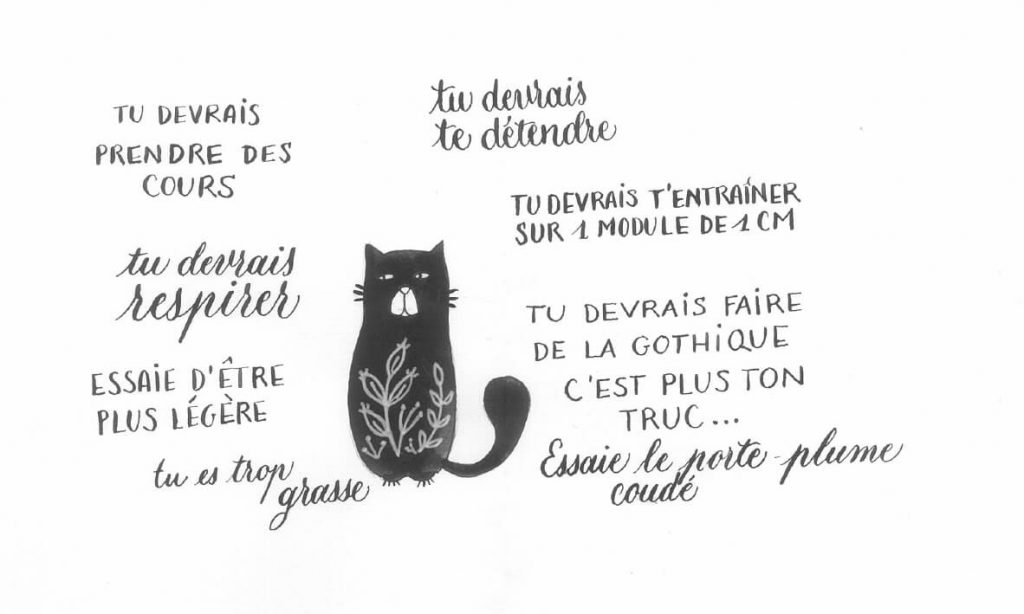
Débuter l’anglaise : quelle encre utiliser ?
Mes premiers pas avec l’anglaise ont été assez désastreux, un peu comme une rencontre qui tourne mal ou un premier baiser qui vous laisse un gout de saucisson dans la bouche. J’aurais pu laisser tomber et retourner à mes écritures gothiques, mais l’appel des volutes aériennes de l’anglaise a été plus fort.
Légèreté, élégance et régularité : voici les maîtres mots pour une belle écriture anglaise, et cela nous fait une belle jambe parce que pour y arriver il faut beaucoup, beaucoup de pratique. On peut donc rajouter « persévérance » !
Les caractéristiques de l’anglaise
Pour mieux comprendre les difficultés du débutant face à l’anglaise, reprenons ses 4 grands principes.
1. Elle est tracée avec une plume pointue
2. Les lettres présentent un contraste plein/délié
3. La forme de base est l’ovale
4. Elle est inclinée, à 54 degrés
Chacune de ces caractéristiques a été pour moi un vrai challenge. Et pour être honnête, mes connaissances des autres écritures ne m’ont pas beaucoup aidée ! Comme je l’ai déjà expliqué dans un article précédent, la première étape a consisté pour moi à :
1. Trouver une plume agréable à utiliser (la Nikko G)
2. M’approprier les pleins et les déliés avec une écriture droite (la Candy Girl).
J’ai ensuite suivi quelques conseils avisés des copines et recommandations lues dans des livres ou sur internet…
L’influence du medium sur l’écriture
Et puis un jour, j’ai compris à force d’essais divers, que l’encre avait une influence déterminante sur le contraste plein/déliés, et sur l’élégance de l’écriture. Avec des plumes larges et biseautées utilisées pour les gothiques ou les onciales, on gagnera en finesse avec une encre bien fluide.
Avec une plume pointue, on aura besoin d’une encre fluide aussi, mais un peu plus consistante, et qui a une bonne adhérence sur la plume (sinon elle coule en grosse goutte et c’est la tâche assurée).
Préparation de la plume
Il faut bien sûr que la plume soit bien propre et dégraissée. Lorsqu’on la trempe dans l’encre, celle-ci doit plus ou moins recouvrir la surface de la plume. S’il y a un effet de goutte d’eau, c’est soit que la plume a encore sa fine pellicule protectrice, soit qu’elle a besoin d’un petit passage dans du fiel de bœuf (ou de la salive tout simplement) pour bien la dégraisser.
Ceci fait, on peut ensuite faire différents tests. Ci-dessous, tout est écrit avec la même plume, sur le même papier : seul le médium change.
Les tests avec divers mediums
1. Encre gallo-ferrique 2. Gouache 3. Finetec 4. Colorex
1. L’encre gallo-ferrique
L’encre gallo-ferrique est fabriquée à partir de noix de galle, d’eau ou de vin, de sulfate de fer et de gomme arabique. On trouve de nombreuses recettes, ou on peut l’acheter toute prête sur les sites qui vendent du matériel de calligraphie.
Cette encre a la particularité d’avoir une grande finesse, une grande élégance. C’est sans doute avec cette encre que l’on obtient les plus beau déliés, fins et aériens.
La plume peut être chargée en la trempant directement dans l’encrier, et en l’égouttant légèrement sur le bord. Il faudra bien rincer et essuyer la plume après usage, car le sulfate de fer est très corrosif.
2. La gouache ou l’aquarelle dilués
La gouache ou l’aquarelle, bien dilués (consistance d’un jus de fruit), offrent un excellent medium pour la plume pointue. Elles contiennent l’une et l’autre un peu de gomme arabique pour une viscosité légère mais nécessaire.
La plume est chargée au pinceau.
3. Les gouaches Finetec Pearl Colors.
Contre toute attente, j’ai eu des résultats exceptionnels avec ces gouaches. Des déliés d’une grande finesse et un très bon confort d’écriture.
4. Les encres aquarelle type Ecoline ou Colorex
Tandis que j’adore ces encres pour les écritures à la plume large ou au ruling-pen, et bien elles sont très décevantes pour l’anglaise. Même avec une addition de gomme arabique, en différentes proportions, le trait reste lourd. L’encre elle-même doit avoir une certaine lourdeur (une charge de pigment peut-être ?) car elle coule beaucoup trop vite dans la plume.
Le résultat est déjà moyen quand on charge la plume au pinceau, mais si en plus on trempe directement la plume dans le flacon, c’est la catastrophe.
5. Les encres pour stylo type Herbin
Même constat qu’avec les encres aquarelles.
Je n’ai pas testé ici d’encres acryliques ou les encres à base de gomme laque comme la Sennelier, car je ne les aime pas… Elle sont beaucoup trop visqueuses à mon goût et encrassent les plumes. Idem pour l’encre de chine, à moins de bien la diluer.
Test avec deux plumes différentes
Ci-dessous un comparatif avec une plume ancienne très fine (« Administrative » de Blanzy Poure) et une Nikko G.
Pour la flamme, oups… désolée mais je ne le fais plus et je ne le recommande pas car cela abîme la plume.Eau, savon, dentifrice, chiffon doux… ou salive si on a rien sous la main !